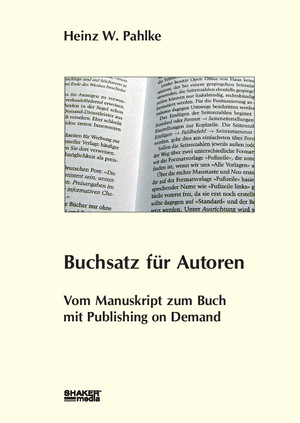
Gestaltung eines Bucheinbands
nachdem ich meinen Buchumschlagsentwurf mit Kollegen diskutiert habe, bin ich genauso schlau wie vorher. Lohnt es sich, an diesem Entwurf weiterzuarbeiten:
Lieber hätte ich "Vom Manuskript zum Buch" als Haupttitel gewählt, aber da es bereits Bücher mit diesem Titel gab bzw. gibt, ist das Risiko zu hoch, dass es rechtlichen Ärger gibt.
Dadurch ist dann aber eben die unterste Zeile mit dem unbefriedigenden Umbruch entstanden. Andere Umbruchvarianten sehen nicht besser aus bzw. sind lesetypographisch unglücklich.
Bei der Schrift handelt es sich übrigens um die Colaborate.
Lohnt es sich, an diesem Entwurf weiterzuarbeiten
Mir gefällt der dem abgebildeten Buch unterlegte 'Umschlag' nicht. Man sieht doch zu deutlich, daß es sich hierbei nur um ein Rechteck mit Füllmuster handelt und nicht um ein 'richtiges' Umschlagpapier.
Die Colaborate mit Ihrem exzentrischen t scheint mit nicht die geeigntete Schrift zu sein, wenn es darum geht, ein Handbuch, wo man auf seriöse Informationen hofft, zu zieren.
Das Bild ist schlecht, langweilig, uninspiriert. Kannst Du nicht eine interessantere ansicht finden? Zur Anregung:
Der Umbruch ist da noch das kleinste Problem. Vielleicht kannst Du den Zweituntertitel etwas entschlacken und mit dem ersten zusammenbringen? Dann könnte beidest kleiner gesetzt werden. Etwa:
Vom Manuskript zum Buch bei book on demand
Man sieht doch zu deutlich, daß es sich hierbei nur um ein Rechteck mit Füllmuster handelt und nicht um ein 'richtiges' Umschlagpapier.
Wie müsste dieses denn aussehen? Ich habe verschiedene Unterlagen probiert. Zum Schluss blieb dann ein Sisal übrig. Papier in verschiedener Ausführung sah mir immer zu glatt und überhaupt nicht papiermäßig aus. Aber vielleicht müsste es nur wesentlich stärker (farblich) strukturiert sein.
Ich würd's gar nicht "strukturieren", sondern einfach eine farbige Fläche einziehen. Ums Bild evtl. einen Rahmen, damit das nicht so schnappschussartig aussieht. Und heys Fotoanregung würde ich aufgreifen; ein Cover sollte mehr zur ästhetischen als zur nüchterninformationsvermittelnden Seite tendieren.
Gegen eine "knackigere" Titelformulierung hätte ich auch nichts, um den passenden (ich nehme mal an kostenfreien) Font zu finden, mal hier blättern:
Die Colaborate mit Ihrem exzentrischen t scheint mit nicht die geeigntete Schrift zu sein, wenn es darum geht, ein Handbuch, wo man auf seriöse Informationen hofft, zu zieren.
Die Colaborate erschien mir gerade besonders geeignet, weil sie eigentlich sehr sachlich, fast schon langweilig wirkt. Wäre da nicht dieses t, hätte ich sie nie ausgewählt.
Aber vielleicht interpretiere ich da auch etwas hinein, was andere ganz anders empfinden.
Das Bild ist schlecht, langweilig, uninspiriert. Kannst Du nicht eine interessantere ansicht finden? Zur Anregung:
Stimmt, auf diese Sicht bin ich nicht gekommen. Ich hatte nur mit einzelnen Buchstaben experimentiert, u.a. auch mit alten Bleisatzlettern. Aber um Schriften geht es nur zum Teil und um Bleisatzlettern überhaupt nicht.
Die Anregung ist jedenfalls gut. Mal sehen, was mir da einfällt.
Vielleicht kannst Du den Zweituntertitel etwas entschlacken und mit dem ersten zusammenbringen? Dann könnte beidest kleiner gesetzt werden. Etwa:
Vom Manuskript zum Buch bei book on demand
Schade, die Idee hätte ich früher gebraucht. Vermutlich lässt sich das nicht mehr ändern. Ich muss mal beim Verlag nachfragen, ob sich da noch etwas machen lässt.
Richtig müsste es aber vermutlich "Vom Manuskript zum Buch mit Book on Demand" heißen.
Ich würd's gar nicht "strukturieren", sondern einfach eine farbige Fläche einziehen. Ums Bild evtl. einen Rahmen, damit das nicht so schnappschussartig aussieht. Und heys Fotoanregung würde ich aufgreifen; ein Cover sollte mehr zur ästhetischen als zur nüchterninformationsvermittelnden Seite tendieren.
Mit einer einfarbigen Fläche hatte ich es als erstes probiert, gefiel mir aber überhaupt nicht. Mit einem anderen Bild könnte es natürlich ganz anders wirken. Werde ich heute abend noch ausprobieren.
Gegen eine "knackigere" Titelformulierung hätte ich auch nichts, um den passenden (ich nehme mal an kostenfreien) Font zu finden, mal hier blättern:
Wie in einem anderen Posting geschrieben, habe ich die Colaborate aber eben gerade wegen dieses t ausgesucht. Als Brotschrift ist sie für ein Sachbuch allerdings wirklich ungeeignet.
Wie müsste dieses denn aussehen?
Einfach wie ein fotografiertes Papier. Da sind die Ränder nicht so glatt, wellen sich vielleicht ein bißchen, das Papier liegt einfach anders da ...